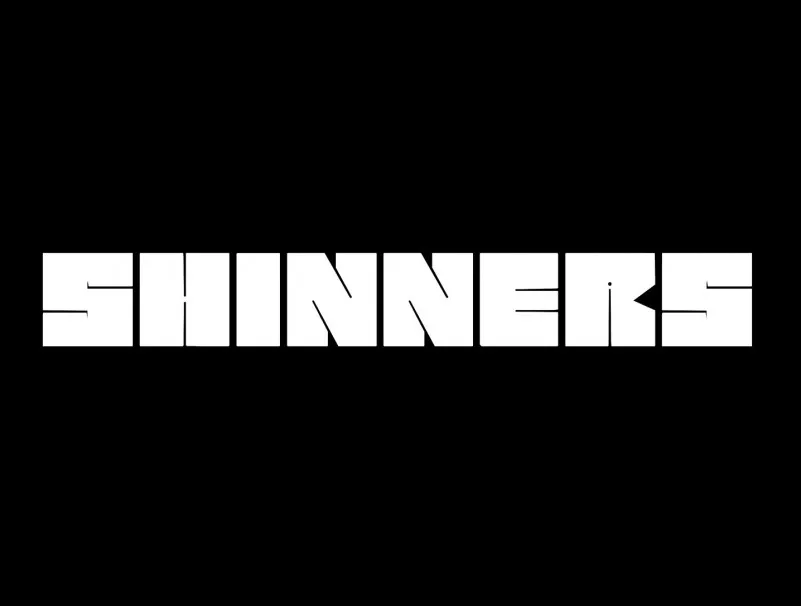
Esta é uma fonte sans-serif geométrica. Introduzimos a Shinners Display Font. A Shinners é uma fonte exibição geometrica com estilo futurista. Esta fonte multi-funcional é ótima para posters, web-design, logomarcas, identidades de marca, embalagens e headlines. A Shinners está absolutamente gratuita tanto para uso comercial quanto pessoal. Então divirta-se e faça belos designs com esta fonte. Uma fonte de destaque sans-serif cheia de coragem ao mesmo tempo elegante e moderno. Perfeita para propósitos tipográficos que exigem uma forte identidade, mas de um modo suave.